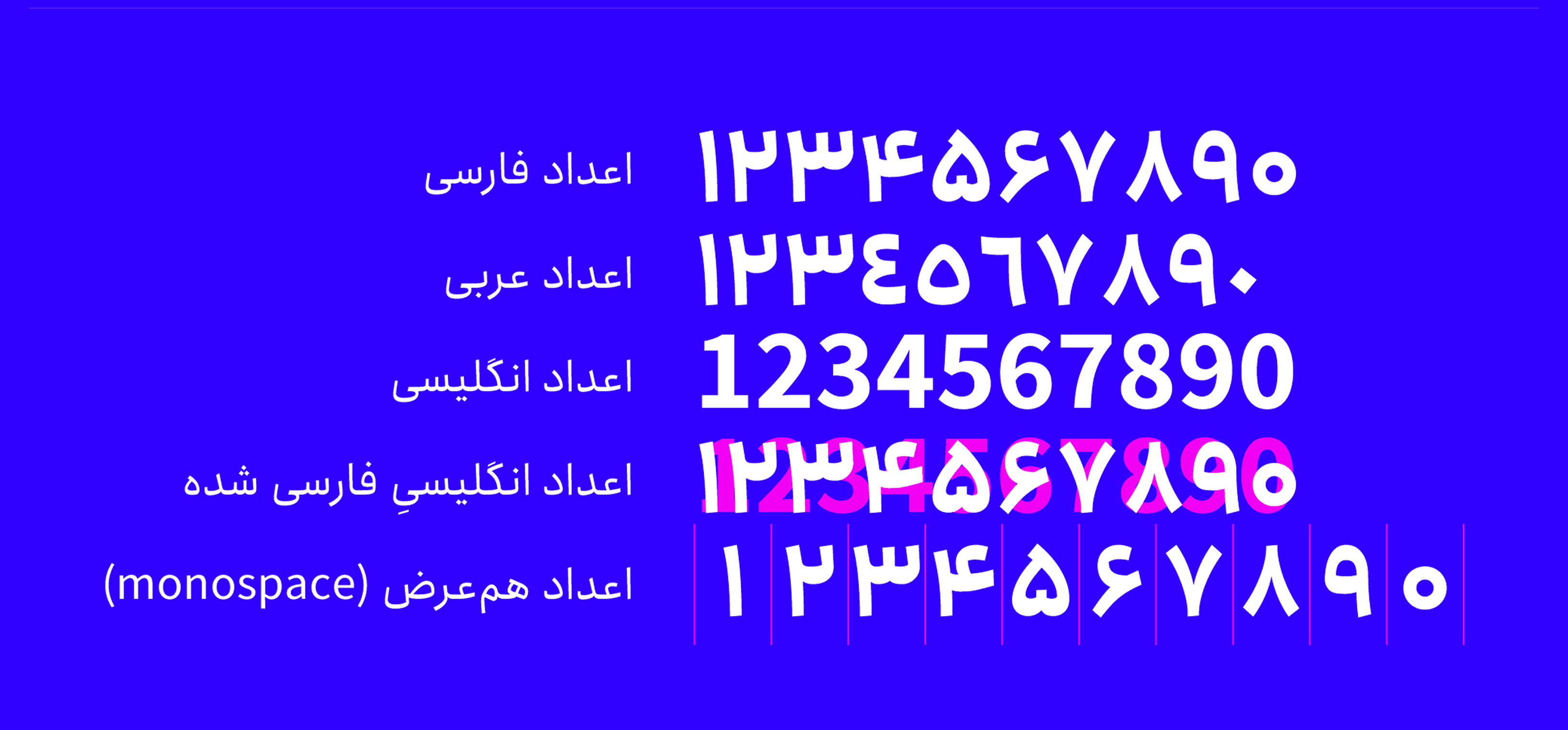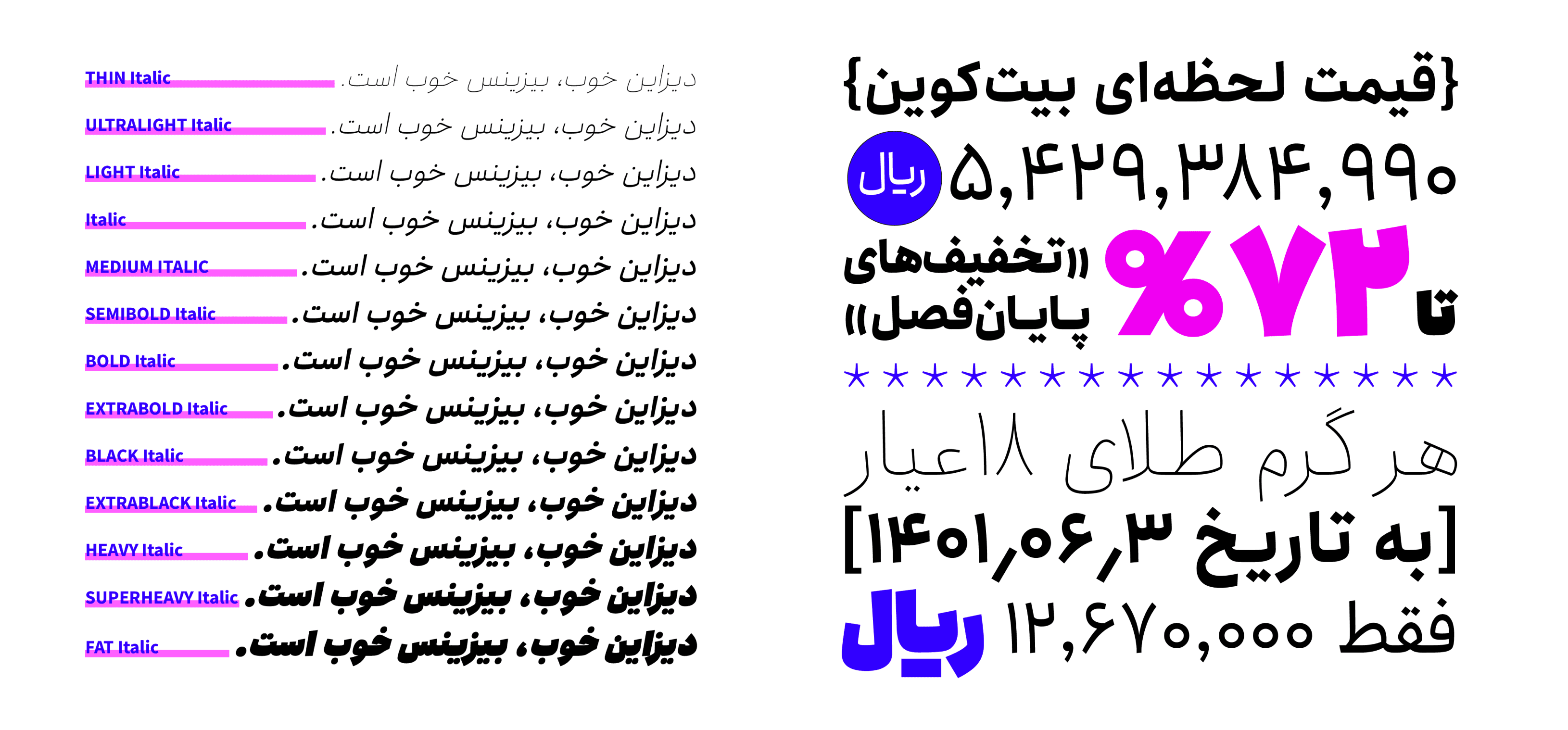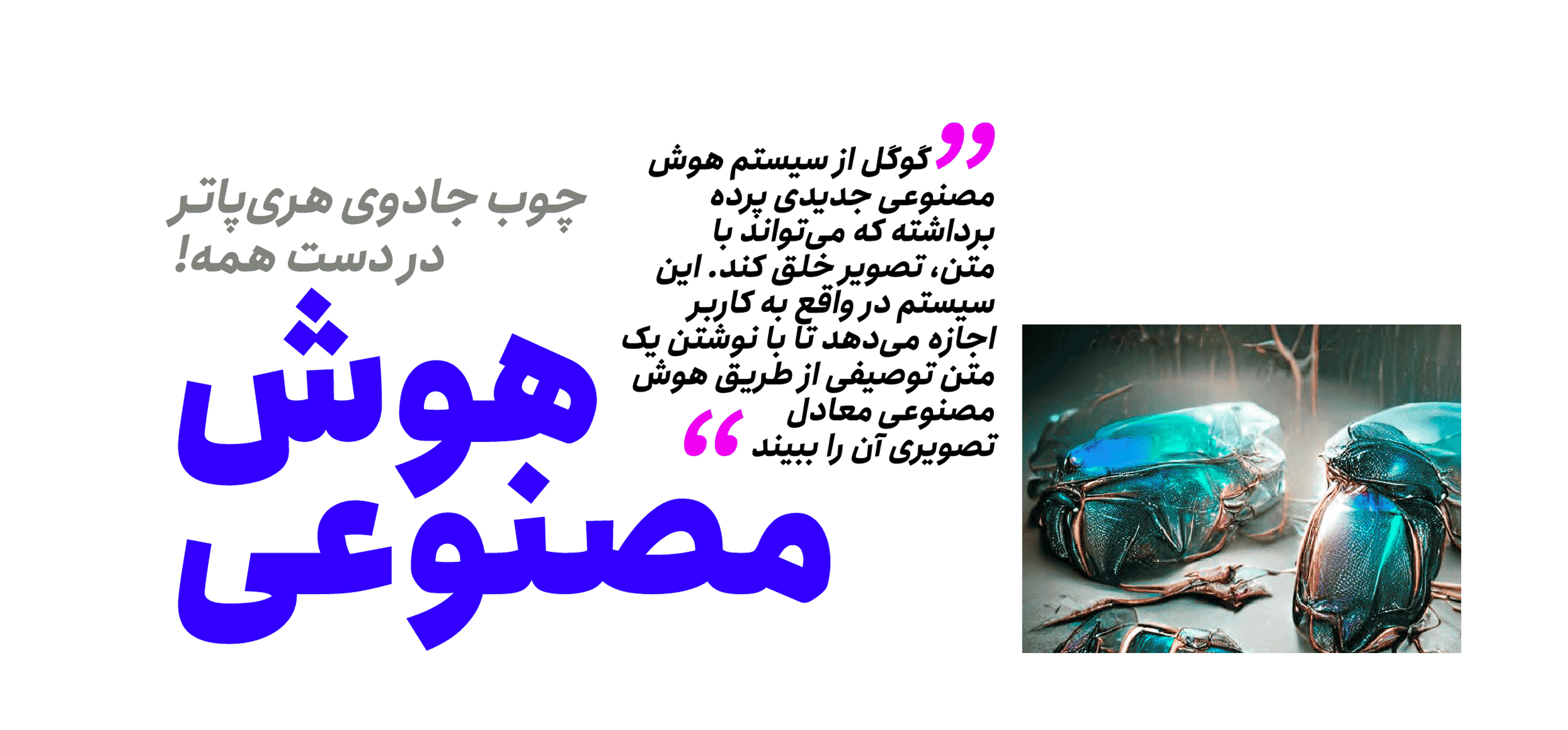
تم تطوير وتحسين خط "أنجمن" ليُستخدم في واجهات المستخدم للتطبيقات والمواقع الإلكترونية، وفي التصاميم البيئية والإعلانات، وتصميم العبوات، والتصميم الطباعي والمطبوعات.
عائلة خطوط "أنجمن" مناسبة للمستخدمين الذين يرغبون في تحقيق عدة أهداف بخيار واحد، إذ توفر مجموعة واسعة من الخيارات للعناوين والنصوص. ولهذا السبب، فقد حظيت باهتمام واعتماد كخط مؤسسي أيضًا.
تم تطوير وتحسين خط "أنجمن" ليُستخدم في واجهات المستخدم للتطبيقات والمواقع الإلكترونية، وفي التصاميم البيئية والإعلانات، وتصميم العبوات، والتصميم الطباعي والمطبوعات.
عائلة خطوط "أنجمن" مناسبة للمستخدمين الذين يرغبون في تحقيق عدة أهداف بخيار واحد، إذ توفر مجموعة واسعة من الخيارات للعناوين والنصوص. ولهذا السبب، فقد حظيت باهتمام واعتماد كخط مؤسسي أيضًا.
تم تطوير وتحسين خط "أنجمن" ليُستخدم في واجهات المستخدم للتطبيقات والمواقع الإلكترونية، وفي التصاميم البيئية والإعلانات، وتصميم العبوات، والتصميم الطباعي والمطبوعات.
عائلة خطوط "أنجمن" مناسبة للمستخدمين الذين يرغبون في تحقيق عدة أهداف بخيار واحد، إذ توفر مجموعة واسعة من الخيارات للعناوين والنصوص. ولهذا السبب، فقد حظيت باهتمام واعتماد كخط مؤسسي أيضًا.